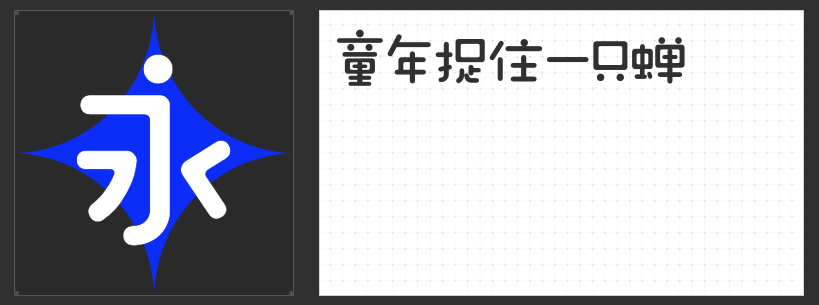
不吃席也能让你的漫展宣传吸引力满满?试试这四款字体吧!
在漫展的多元宇宙中,视觉设计是连接虚拟与现实的桥梁。无论是海报、场刊、应援物还是舞台背景,字体的选择都需兼顾个性表达与氛围营造。以下四款风格鲜明的字体,以独特的手写感、趣味结构与动态张力,为漫展设计注入鲜活生命力。
一、字恋狂澄空 絮风
这款字体以自然手写为基底,通过“上松下紧”的错落布局与低重心设计,打破传统字型的刻板印象。笔画粗细均匀却暗藏巧思——流畅的弧线与利落的直线交织,折笔处采用平直切角弱化锐度,既保留书写温度,又赋予现代简约感。字间距的精密计算让文字组合如音符般富有韵律,尤其适合需要传递轻松氛围的漫展主题标语或角色台词设计。
二、字恋狂饼干棒简 粗体
灵感源自童趣零食的“饼干棒”字体,以颠覆常规的笔画结构制造惊喜。例如“圆”字外框一笔画成,倒梯形轮廓与开口设计打破汉字固有形态,搭配圆润的笔画末端,瞬间唤醒观众童心。这种看似随意却精心设计的“不完美感”,恰好契合漫展对二次元文化中“打破次元壁”的追求,是萌系IP或搞笑漫画展区的绝佳选择。
三、励字造桃气圆 常规
作为手写圆体的代表,这款字体以“松弛感”为核心设计语言。笔画如棉花糖般柔软舒展,内外圆角折笔与圆形元素替代笔画的设计,让文字仿佛自带柔光滤镜。断笔处理不仅提升阅读流畅度,更营造出轻盈的空气感,非常适合少女向动漫展、甜品主题摊位或温馨向同人志封面,传递治愈系视觉体验。
四、字恋狂嗨玩简
粗壮的方块字形与低重心设计,让这款字体自带“憨厚可爱”的标签。笔画如积木拼接般简洁有力,刻意放大的转角与留白,强化了字体的玩具属性。无论是用于游戏展区的巨型标题,还是cosplay摄影区的趣味标语,其“笨拙感”都能巧妙消解距离感,激发观众的互动欲望。
漫展设计的精髓在于用视觉语言构建沉浸式体验,而这四款字体通过结构创新、笔画游戏与情感传递,为设计师提供了突破常规的创意工具。它们不仅是文字的载体,更是连接观众与虚拟世界的情感纽带——让每一处文字细节,都成为漫展宇宙中闪耀的星辰。